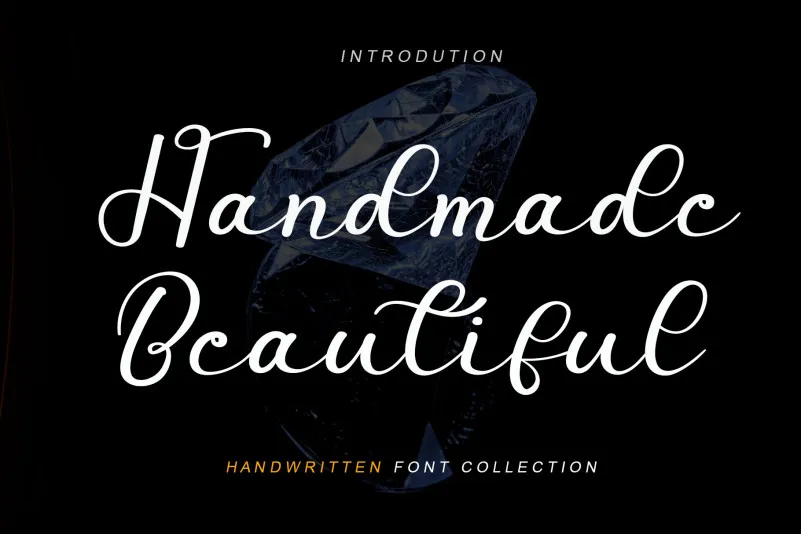
Handmade Beautiful Font – Download Grátis
Esta fonte Script é uma delicada e refinada escolha para quem valoriza elegância e sofisticação. Ela tem alternativas estilizadas e ligaturas que adicionam um toque único, tornando-a perfeita para qualquer projeto gráfico. Suas linhas finas e detalhes sutis criam um resultado visual encantador, ideal para textos legíveis e elegantes. Seja em uma assinatura personalizada ou em um design editorial, essa fonte é certamente uma opção a ser considerada para dar um toque final incrivelmente sofisticado aos seus projetos. Com o designer kateengciu à frente, você terá uma fonte de qualidade que se destaca no mercado de script fonts.